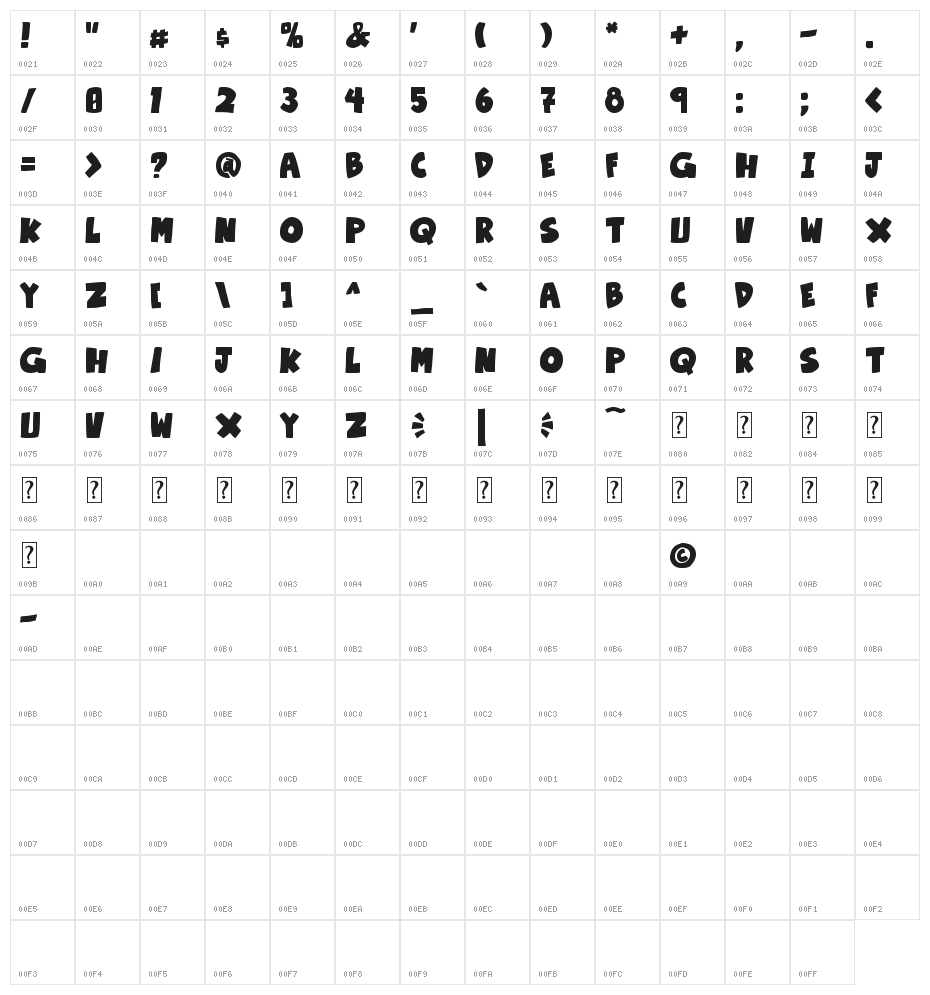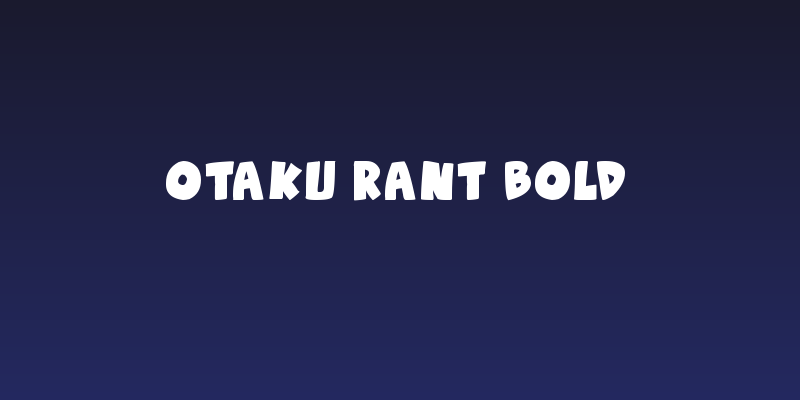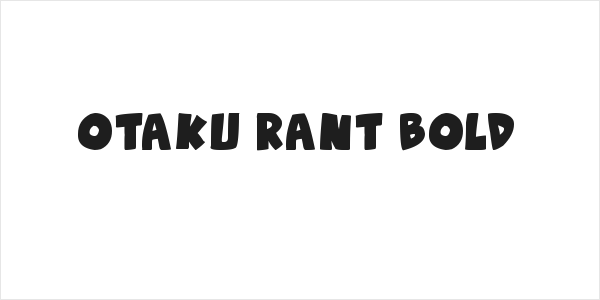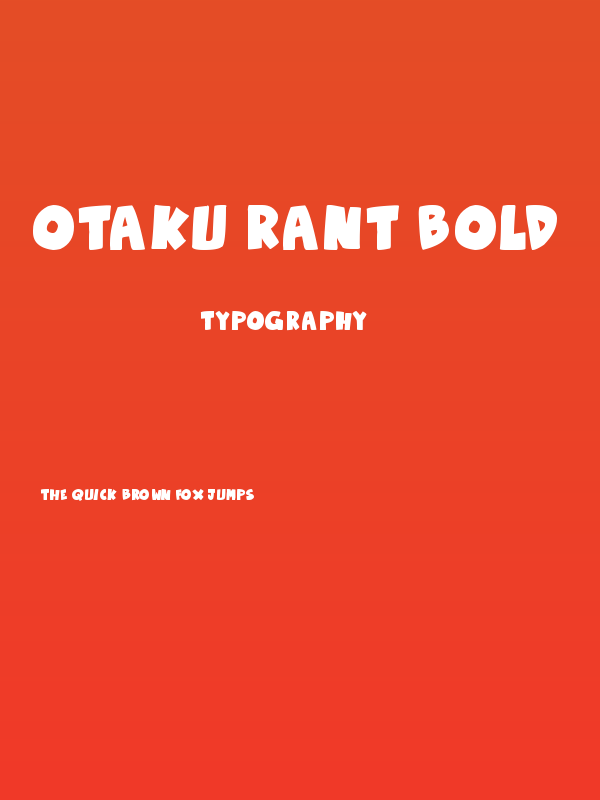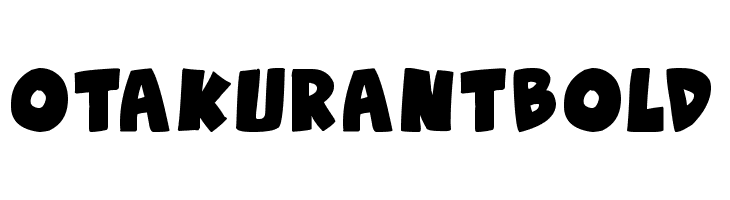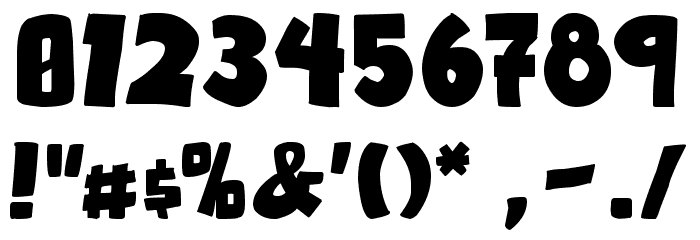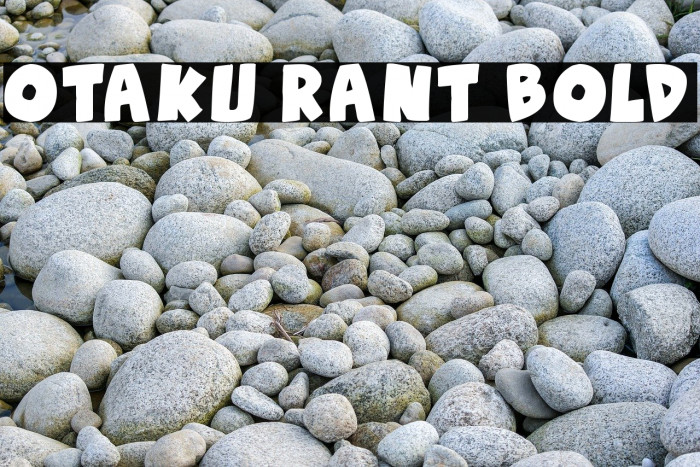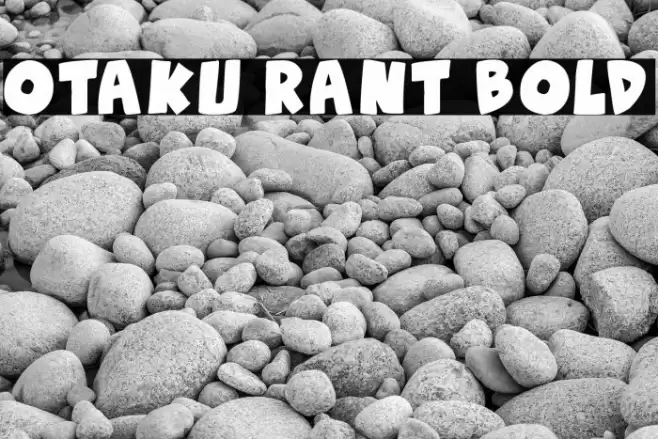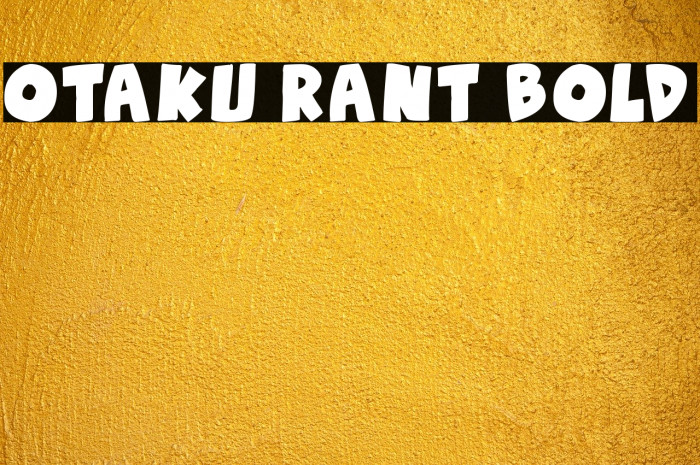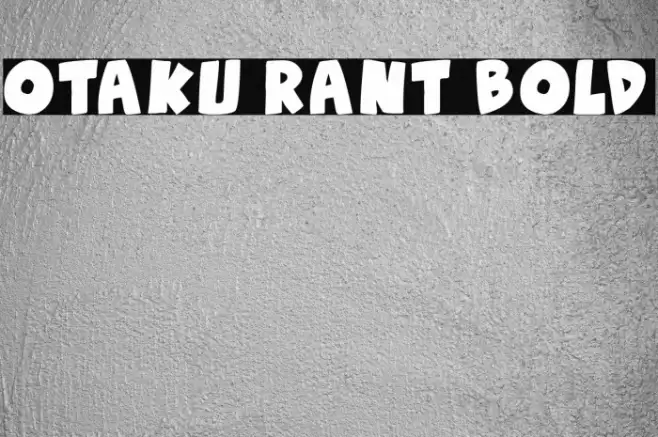
Otaku Rant Bold Font
| समग्र शैली | Playful, Cartoonish |
| उपयोग का मामला | Headlines, Logos, Posters |
| सुझाए गए प्रोजेक्ट | Perfect for children's books, comic strips, playful branding, and eye-catching posters. |